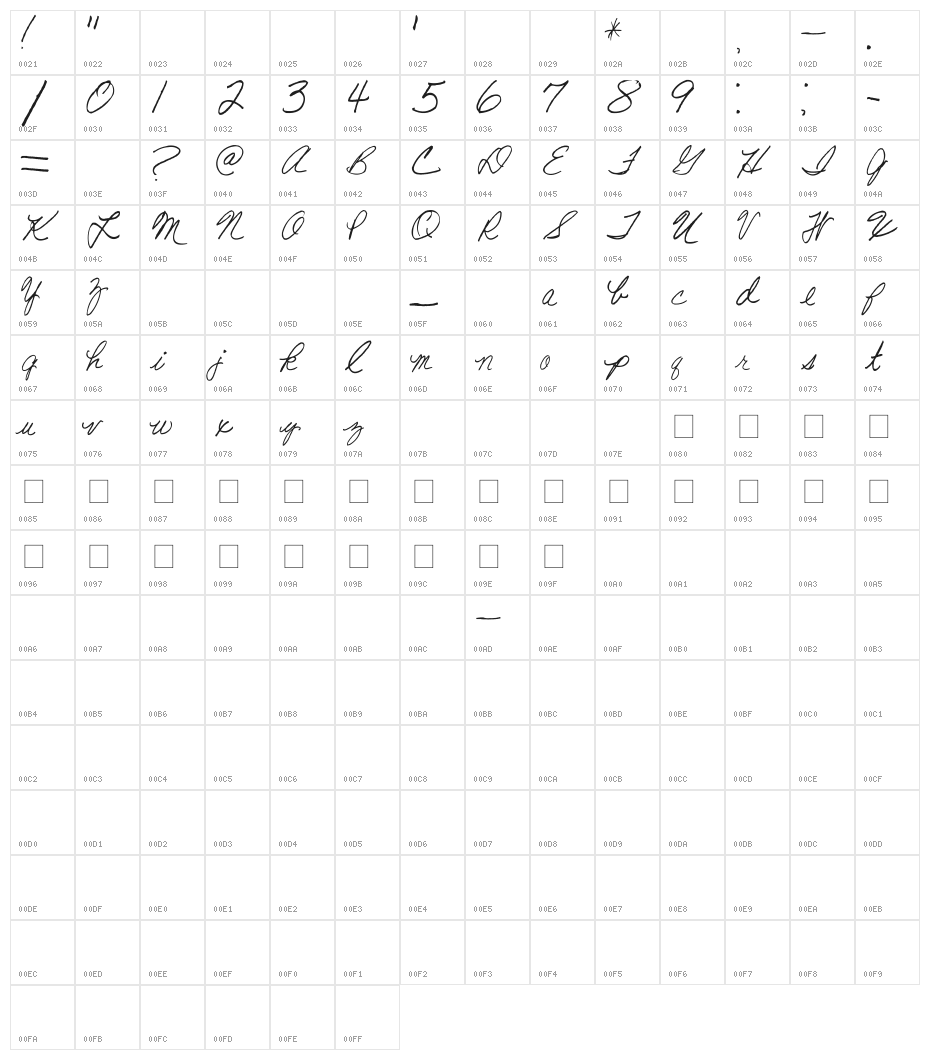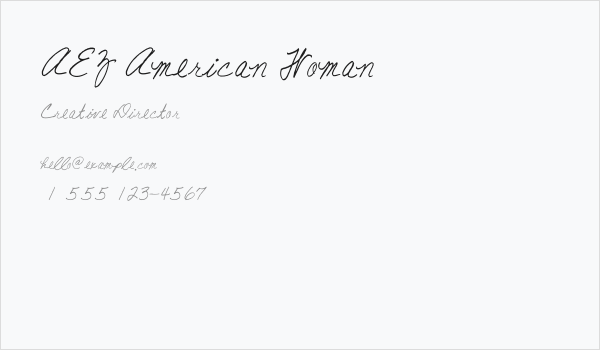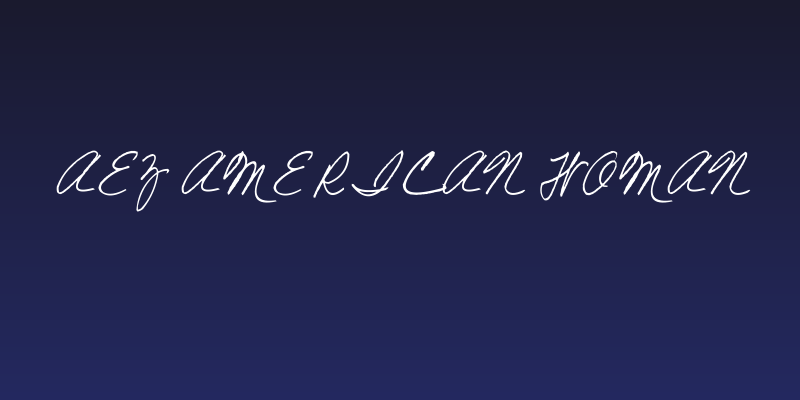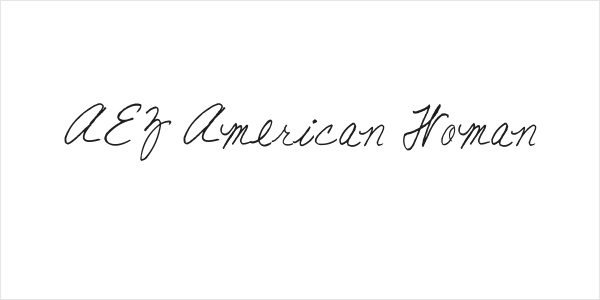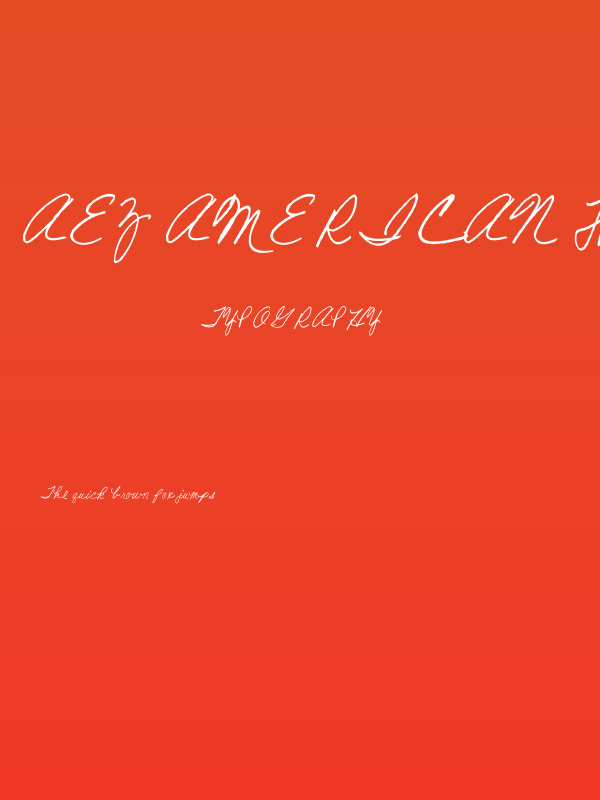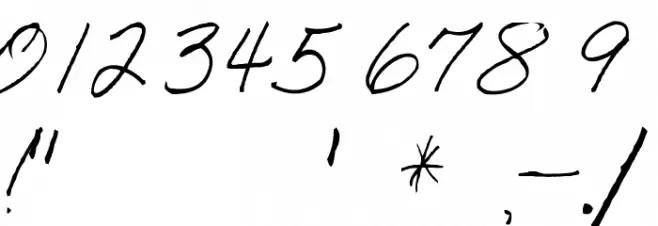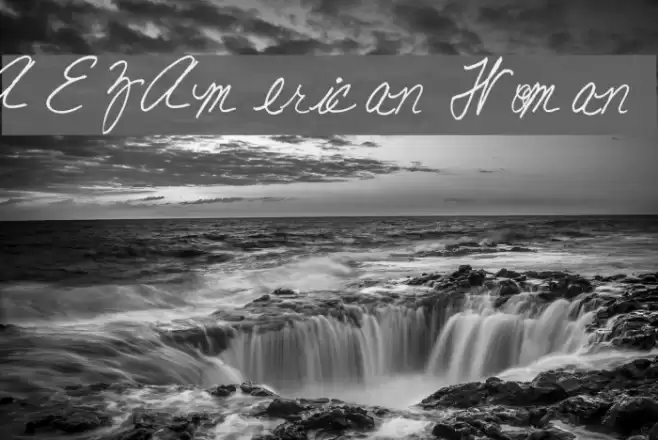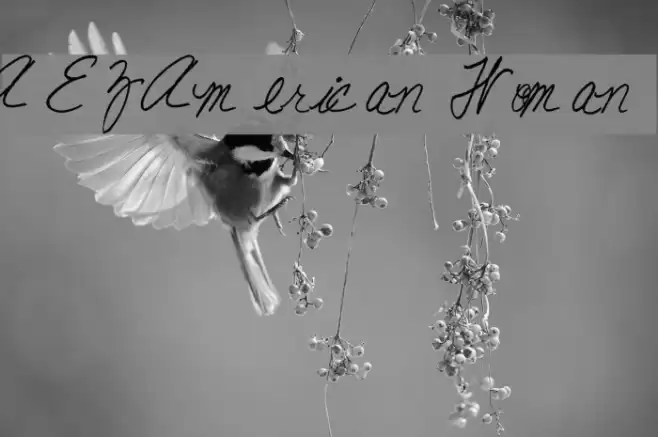
AEZ American Woman Font
| حالة الاستخدام | Logos, Invitations, Artistic projects |
| مشاريع مقترحة | Ideal for personal invitations, artistic branding, and creative projects that require a personal touch. |